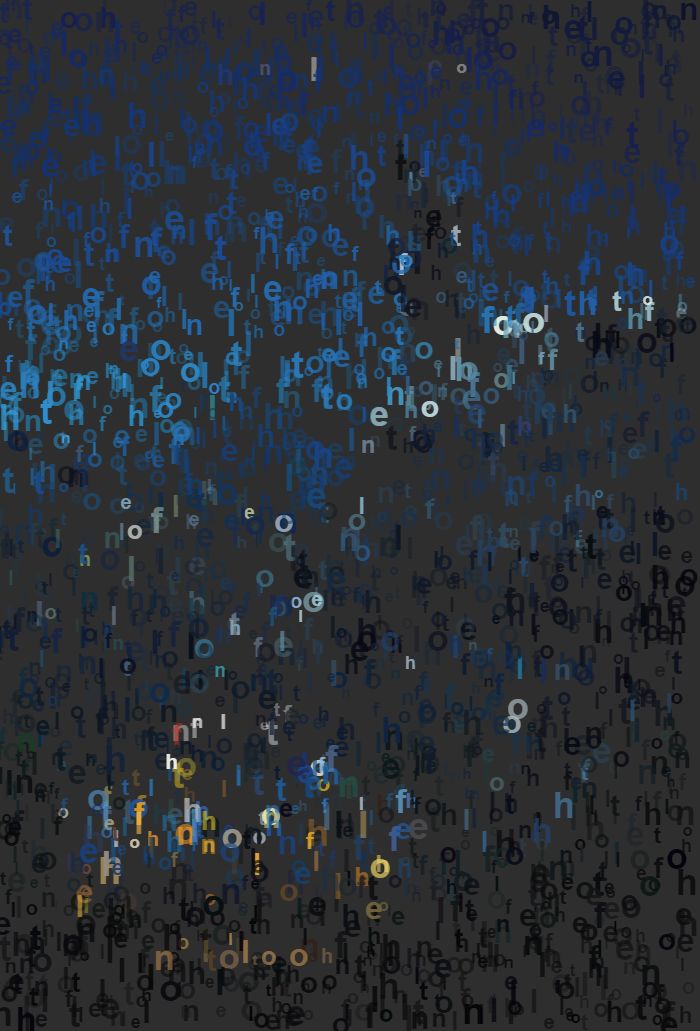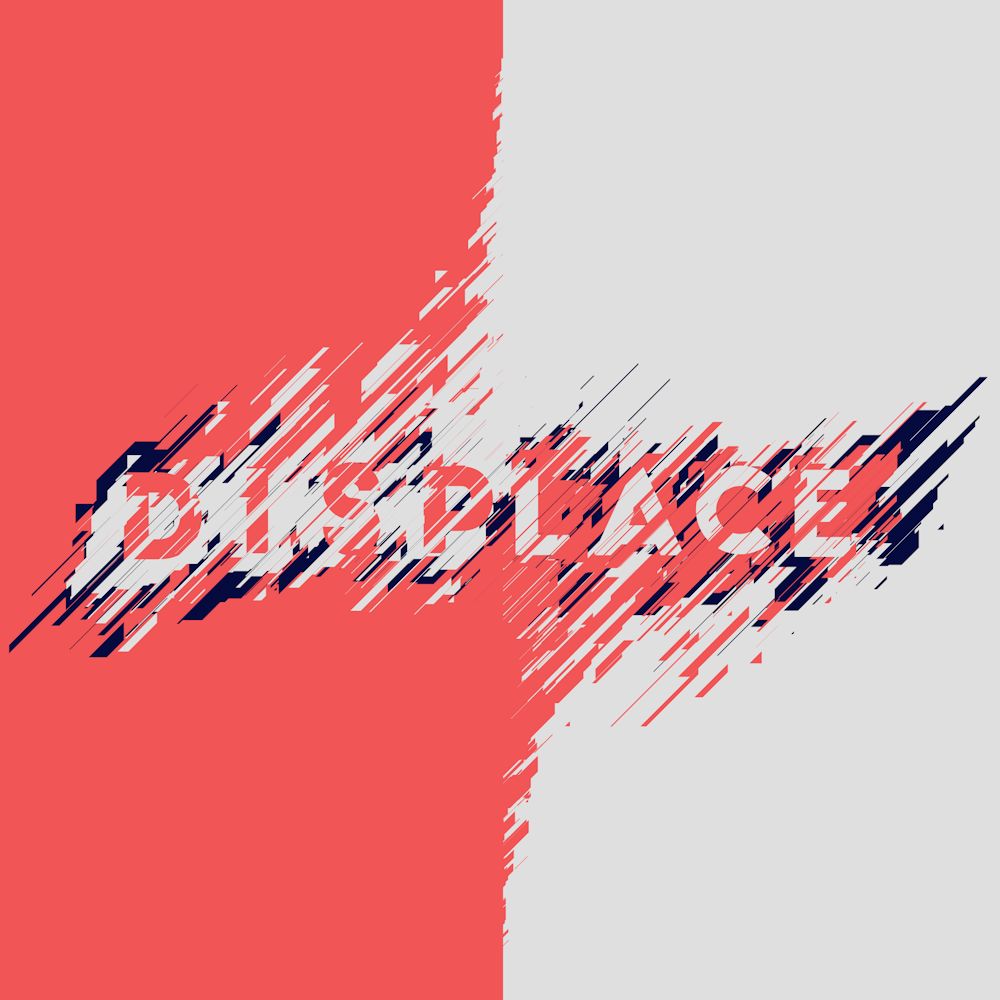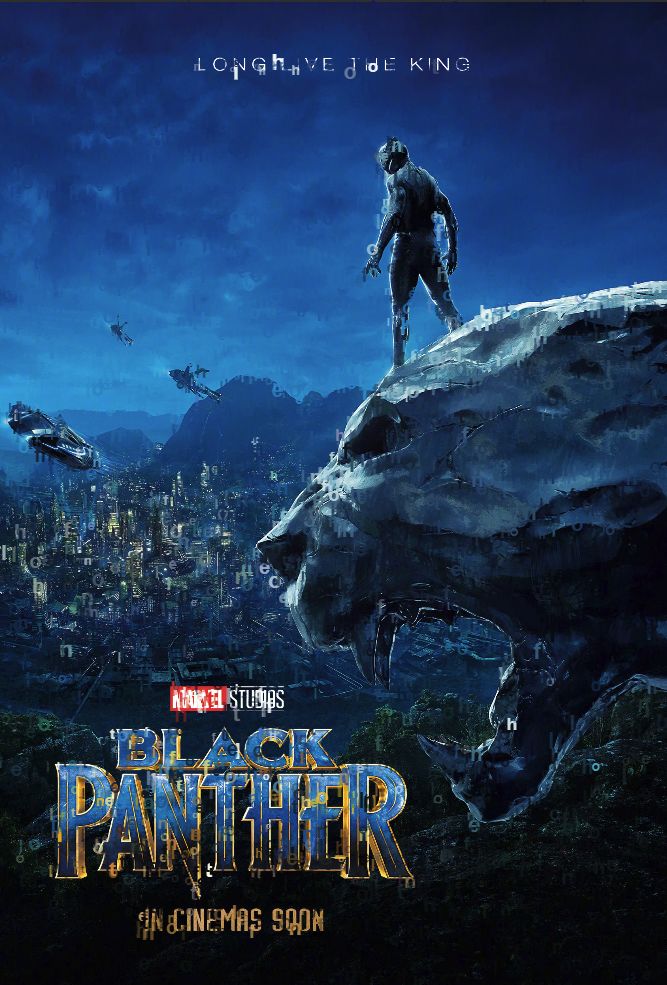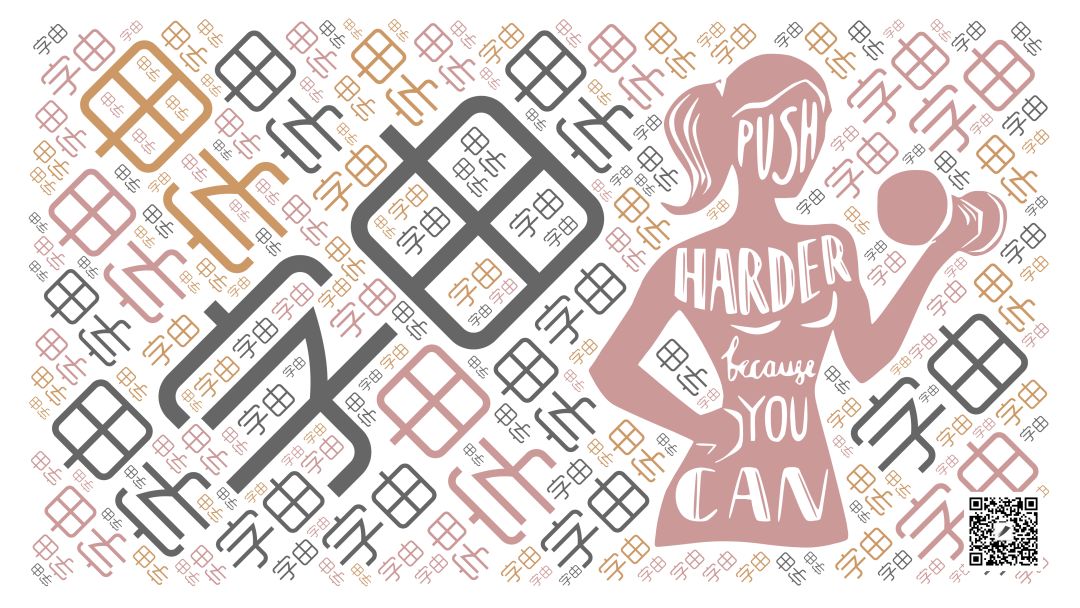
设计特效网站盘点,分享几个好用的特效网站
之前在都说流浪地球NB,可除了科幻,它的融入感更值得偷师~说过,文字不应该是排版的最后一步,而是一开始就融合进去,下面这些网站不光给你灵感,还能一键生成。
http://tholman.com/texter/
这种文字环绕的海报,你一定见过,但ps做有点费劲,像这样拿鼠标就能画,岂不是很方便。
还可以调颜色,大小。
既然可以写字,画别的图形应该也可以,这就有了更多可能性。
文字图形混一下血如何?
http://gogoame.sumbioun.com/
这是一个启发灵感的网站,文字随着雨滴慢慢滑下,很是浪漫~
我试着输入“hellofont”,它会以单个字母出现,再慢慢拼成一起。
所以在排版上,你也可以大珠小珠落玉盘~
或者再发散一下,不走寻常轨。
http://textify.it/
有没有想过,把文字当成碎片,拼成一幅画?找昨天的海报试试~
远看像是被马赛克了一样,但仔细看都是文字,你可以调整字符集、比例。
也可以让它看起来像被“黑客”了……
其实这种效果在海报中也似曾相识。
http://word2art.com/
最后这两个网站相当有用,选好你想要的效果,就能直接生成文字云。
我随便选了一款,就做成了这样,还不错吧!
https://wordart.com/
第二个以英文为主,你也可以去玩玩~
之前也发过这个图,非常经典。